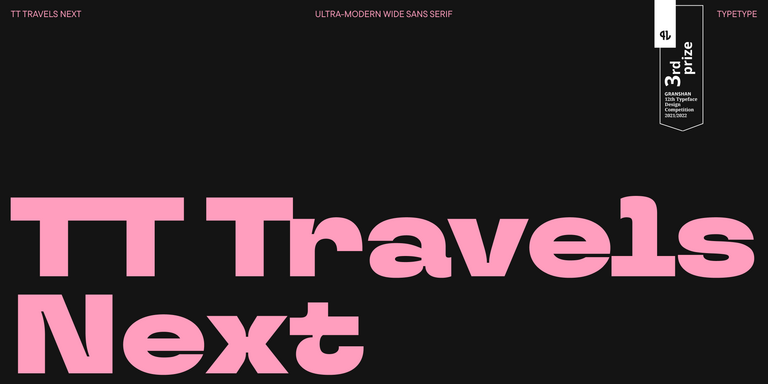
TT Firs Neue es una reinterpretación contemporánea de la clásica sans serif TT Firs.
Fuentes similares a Architype Ingenieur
Si estás cansado de las fuentes desgastadas y busca tipos de letra similares a Architype Ingenieur, consulta nuestras principales alternativas a Architype Ingenieur. Estas son fuentes que tienen características similares, pero al mismo tiempo tienen características de diseño nuevas y únicas. Por ejemplo, pertenecen a la misma categoría de fuentes, son adecuadas para los mismos fines y tienen características similares, pero difieren en detalles o proporciones.
En TypeType encontrarás fuentes de vanguardia, tales como Architype Ingenieur e incluso mejores: aquí hay algunas alternativas excelentes y menos comunes a Architype Ingenieur. Utiliza esta lista de fuentes de alta calidad con apariencia Architype Ingenieur que se adapten a tus gustos. De esta manera podrás elegir una fuente aún más adecuada para tu proyecto, ampliar la selección o actualizar tu diseño. Todas las fuentes que aparecen en esta colección están disponibles en diferentes formatos y a precios asequibles, por lo que podrás encontrar una que se adapte a cada necesidad.
Encuentra un excelente reemplazo para Architype Ingenieur e intenta emular un estado de ánimo similar usándolo en sus diseños. Cada fuente presentada en esta página es un doble de la fuente Architype Ingenieur, de hecho, su análogo completo.
TT Fors es una moderna sans serif geométrica con caracteres y formas de anchuras contrastantes.
TT Gertika es una sans serif geométrica con un carácter dinámico y un ritmo danzante. La idea de esta tipografía proviene de los rótulos presentes en un cartel estadounidense de finales de los años 30.
TT Cometus es una tipografía expresiva que cautiva desde el primer instante.
TT Travels Next es una moderna y muy actual sans serif display de gran anchura, diseñada para utilizarse tanto en medios impresos como digitales.
TT Rounds Neue es una familia tipográfica sans serif suave, amigable y redondeada.
TT Autonomous es una moderna sans serif techno con amplias proporciones angulares.